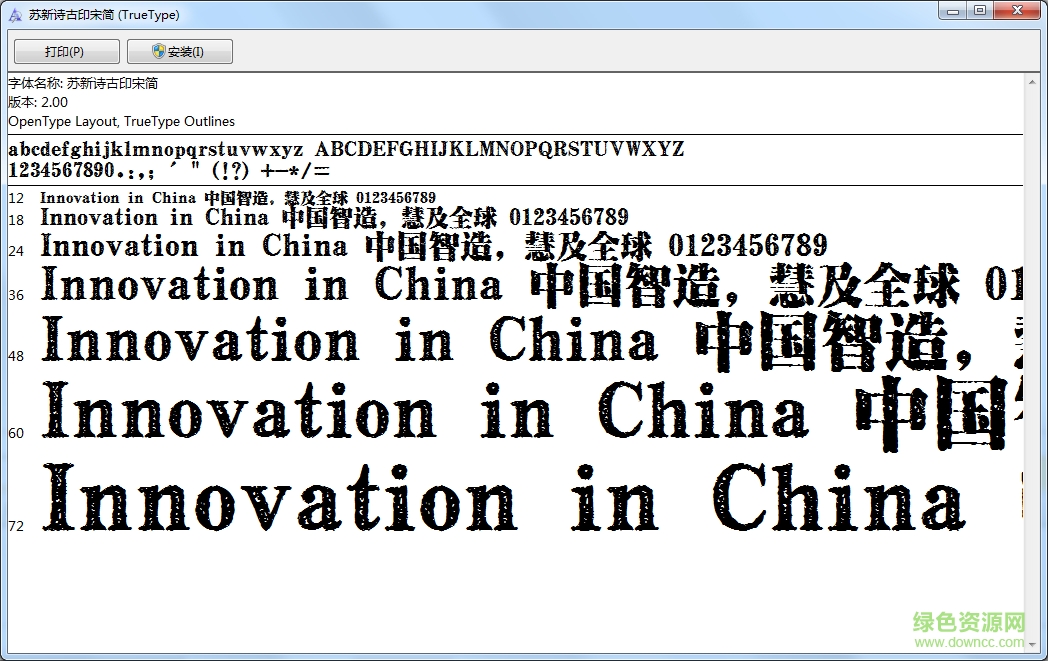
軟件介紹 軟件標簽: 蘇新詩 字體 蘇新詩古印宋簡是一款非常好用的藝術字體,由于字體以宋體為主體,所以字形非常的工整,再加以古色古香以及有點虛線和縫隙的古印手法,非常的大氣自然,喜愛的朋友趕快到綠色資源網下載使用吧!使用方法1.首先選中你下載的打包字體,并解壓你下載的字體壓縮包。2.Win Vista\Win 7\Win 8系統(tǒng):鼠標右鍵單擊字體文件,然后點擊 > "Install" 安裝字體 3.Windows XP(2000\98)系統(tǒng):把解壓好的字體文件放入 C:\Windows\Fonts 目錄中即可 軟件截圖 上一張下一張(1 / 1) 安裝詳細截圖 猜你喜歡 蘇新詩 古印體 蘇新詩 蘇新詩字體是一款收錄了蘇新詩個人創(chuàng)作的所有字體合集,包括蘇新詩卵石體、蘇新詩柳楷簡、蘇新詩古印宋簡、蘇新詩毛糙體等多款字體,字體兼具藝術字體和手寫字體的獨特風格,給人書寫流暢、大方美觀的視覺體驗,歡迎大家來綠色資源網免費體驗! 查看更多>> 蘇新詩指畫體字體 1.87M/中文/6.6/下載 蘇新詩字體合集(10款) 33.98M/中文/5.0/下載 蘇新詩鼠標行書簡體 5.01M/中文/3.3/下載 蘇新詩雙勾體字體 2.71M/中文/10.0/下載 蘇新詩古印宋繁體 5.34M/中文/0.0/下載 蘇新詩卵石體 1.24M/中文/5.0/下載 古印體 古印體是一款非常有特色的字體,古印體字體集合是由綠色資源網小編精心為大家整理的古印體字體大全,包含了各種類型的古印字體,每款字體都各具特色,古風韻味十足,喜歡這款字體的朋友可以來綠色資源網下載使用。 查看更多>> 古印加祖瑪手機版(Candy Rush Zuma) 13.50M/中文/6.6/v1 安卓中文版下載 cguyinhks bold蒙納簡古印體 4.91M/中文/5.0/下載 datx2 5.59M/中文/4.2/下載 青鳥華光淡古印繁體 4.04M/中文/10.0/下載 青鳥華光簡淡古印字體 3.79M/中文/10.0/下載 tankuineg-bold-t-gb字體 4.88M/中文/2.8/下載 其他版本下載 標題 大小 更新日期 下載 下載地址 電腦版 蘇新詩古印宋簡字體 點擊報錯 軟件無法下載或下載后無法使用,請點擊報錯,謝謝! 關閉報錯反饋 請描述您所遇到的錯誤,我們將盡快予以修正,謝謝! *必填項,請輸入內容 本類最新 dreamweaver字體庫 首爾南山體字體 v1.06 官方版 潮字社風云簡ttf 潮字社凌渡鯤鵬簡體字體 潮字社曾玉波手書簡字體 微博慧心字體 相關文章 Photoshop字體安裝使用方法和技巧 如何解決“無法新增字體”問題 Win 7系統(tǒng)安裝字體方法 網頁字體大小設置方法 怎么改網頁字體大小 在Linux系統(tǒng)中安裝字體的幾種方法 windows7字體顯示問題:打開某些程序的時候顯示的是亂碼 用戶評論 熱門評論 最新評論 發(fā)表評論 查看所有評論(0) 昵稱: 請不要評論無意義或臟話,我們所有評論會有人工審核. 字數: 0/500 (您的評論需要經過審核才能顯示)